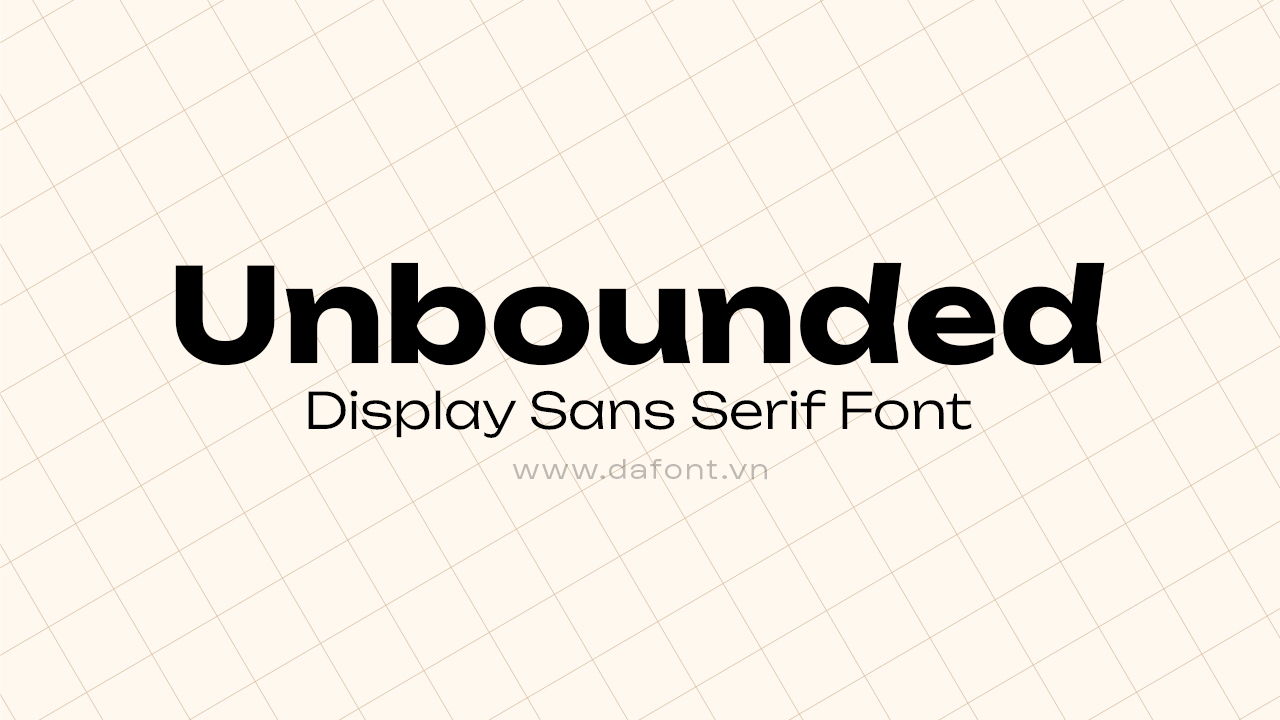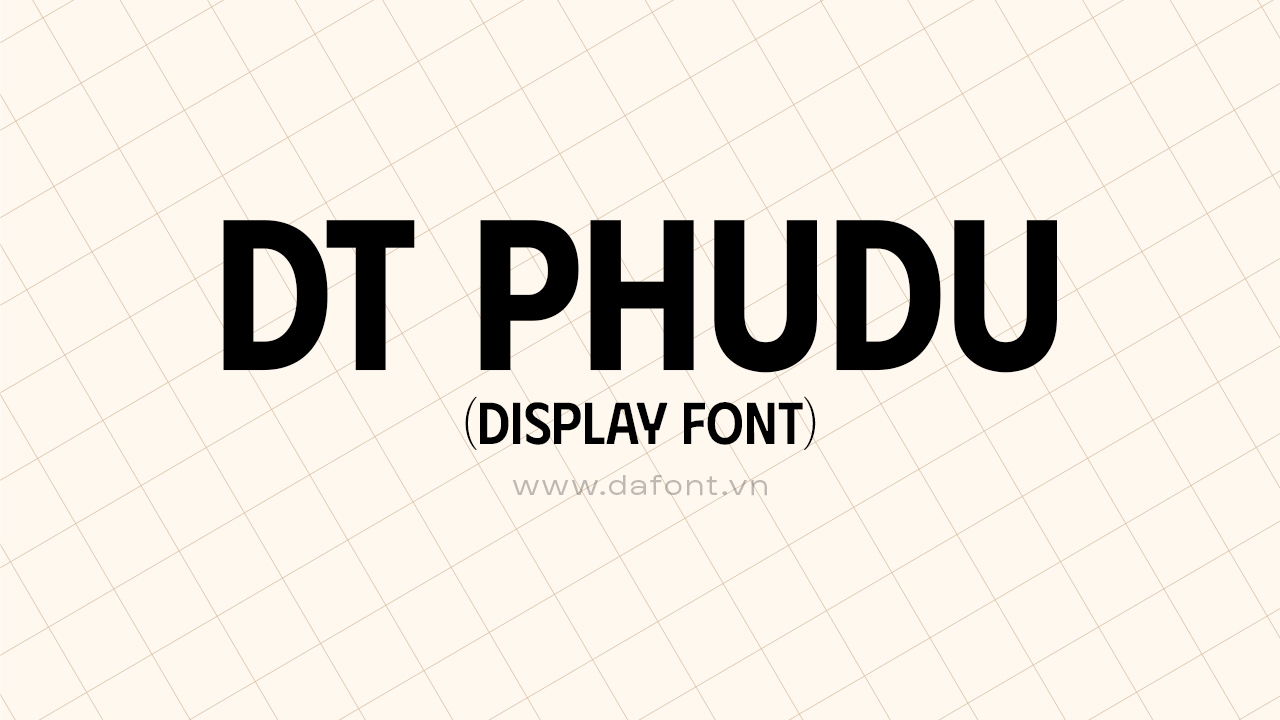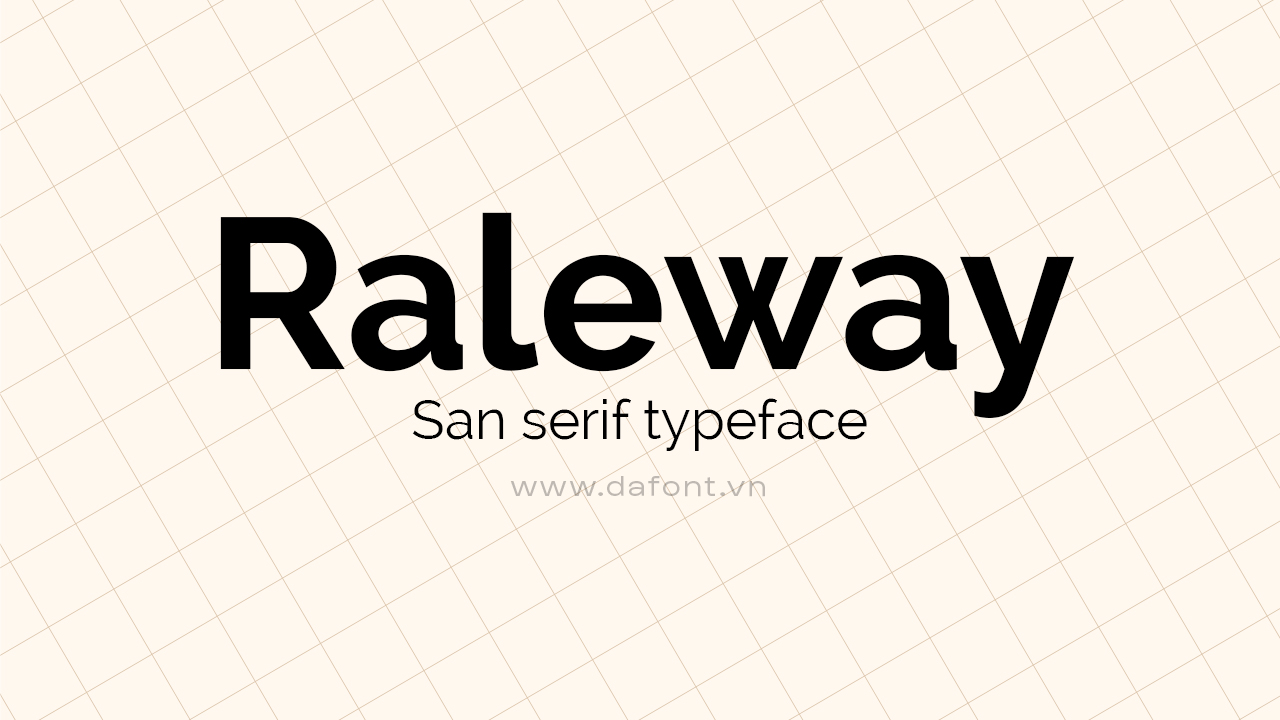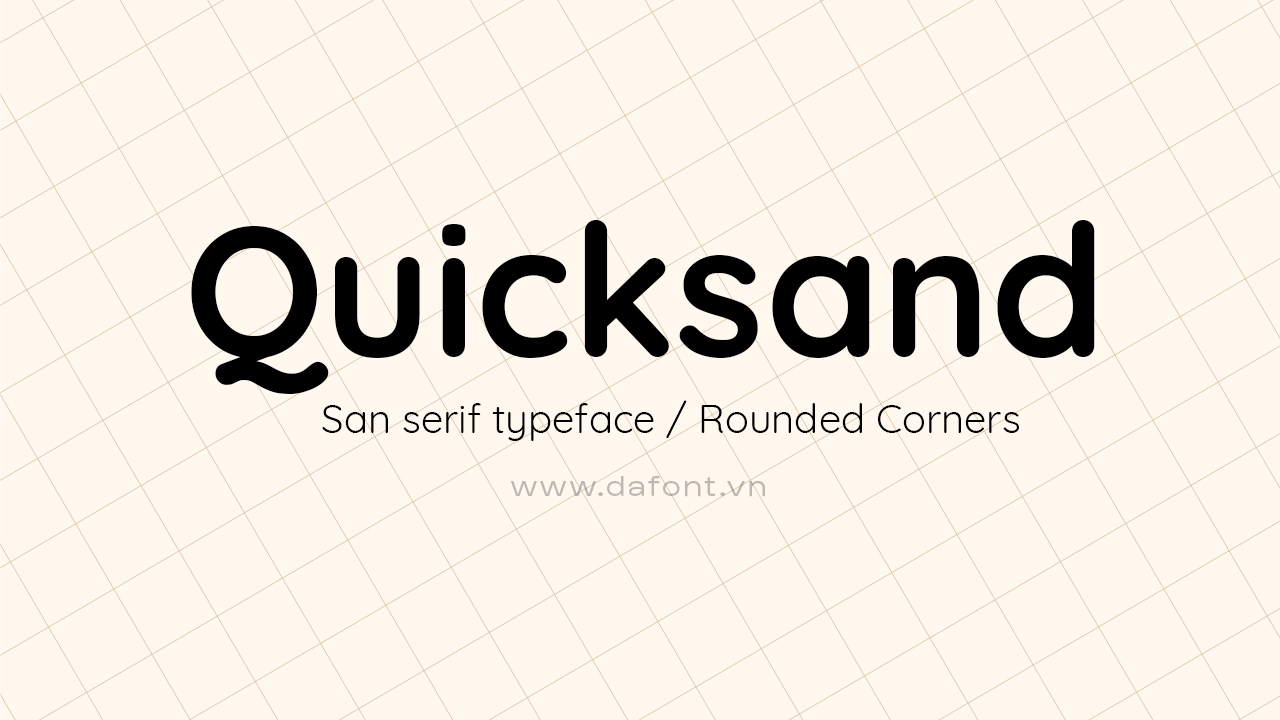
Trong thế giới thiết kế đồ họa, việc lựa chọn font chữ phù hợp không chỉ truyền đạt thông điệp một cách rõ ràng mà còn thể hiện phong cách và bản sắc riêng của thương hiệu. Google Fonts là một kho tàng font chữ miễn phí trở thành một nguồn tài nguyên vô giá cho các nhà thiết kế. Đặc biệt, với sự gia tăng của nội dung tiếng Việt trên internet, việc lựa chọn những font chữ hỗ trợ tiếng Việt là điều không thể thiếu. Vậy, font tiếng Việt nào thống trị Google Fonts. Hãy cùng khám phá nhé.
Google Fonts là gì?
Google Fonts là thư viện font chữ miễn phí được cung cấp bởi Google. Ra mắt vào năm 2010, nó đã nhanh chóng trở thành một công cụ quan trọng cho các nhà thiết kế web, nhà phát triển, nhà sáng tạo và cho bất kỳ ai muốn cải thiện giao diện văn bản trên các trang web, tài liệu, ứng dụng.
Những bộ font tiếng Việt phổ biến trên Google Fonts
Ngoài những font tiếng Việt đang thống trị Google, bạn cũng có thể khám phá nhiều font Việt hóa đẹp mắt, mang đến phong cách độc đáo và cá tính cho thiết kế của mình. Những font này không chỉ giúp nội dung trở nên sinh động, mà còn phù hợp với xu hướng thiết kế hiện đại, hỗ trợ đầy đủ dấu tiếng Việt để bạn thoải mái sáng tạo.
1. Montserrat
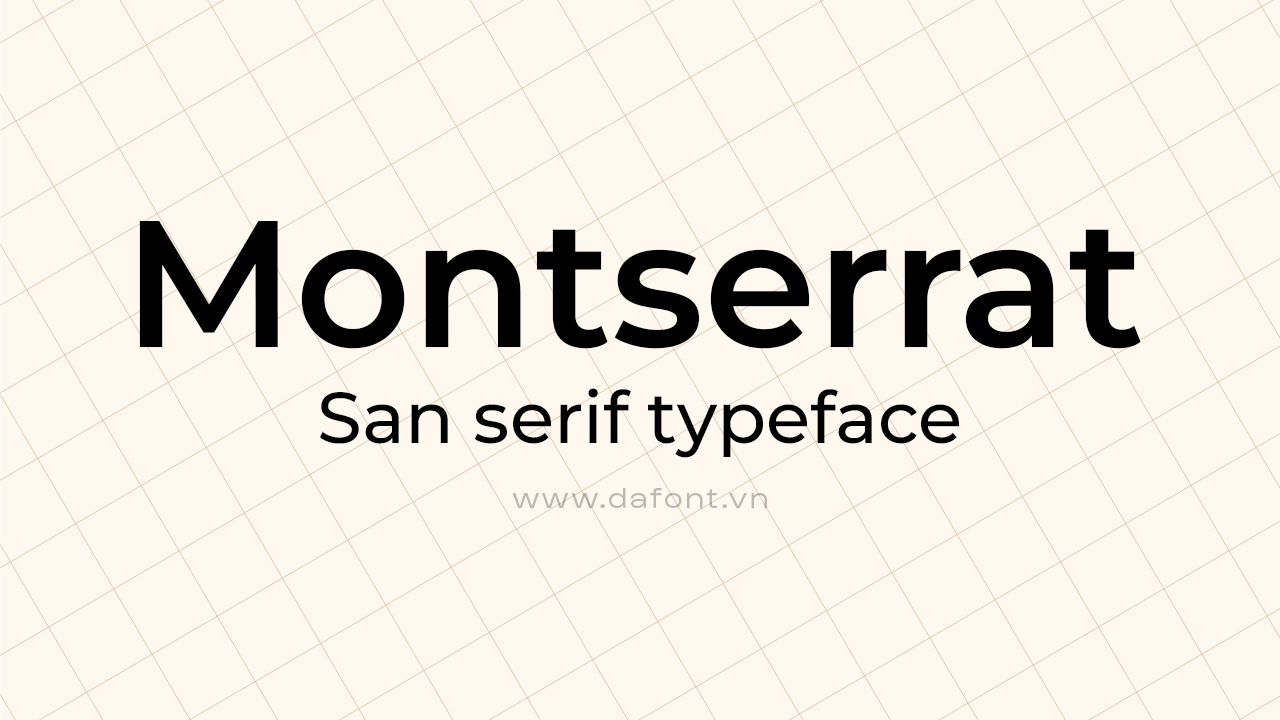
Montserrat là font chữ sans-serif hiện đại được thiết kế bởi Julieta Ulanovsky. Lấy cảm hứng từ các bảng hiệu và áp phích cổ điển ở khu phố Montserrat của Buenos Aires, Argentina. Font chữ này mang đến sự hòa quyện giữa vẻ đẹp truyền thống và tính thẩm mỹ hiện đại. Montserrat bao gồm 18 font và là một trong những bộ font chữ được ưu chuộng nhất trên Google Fonts.
2. Nunito
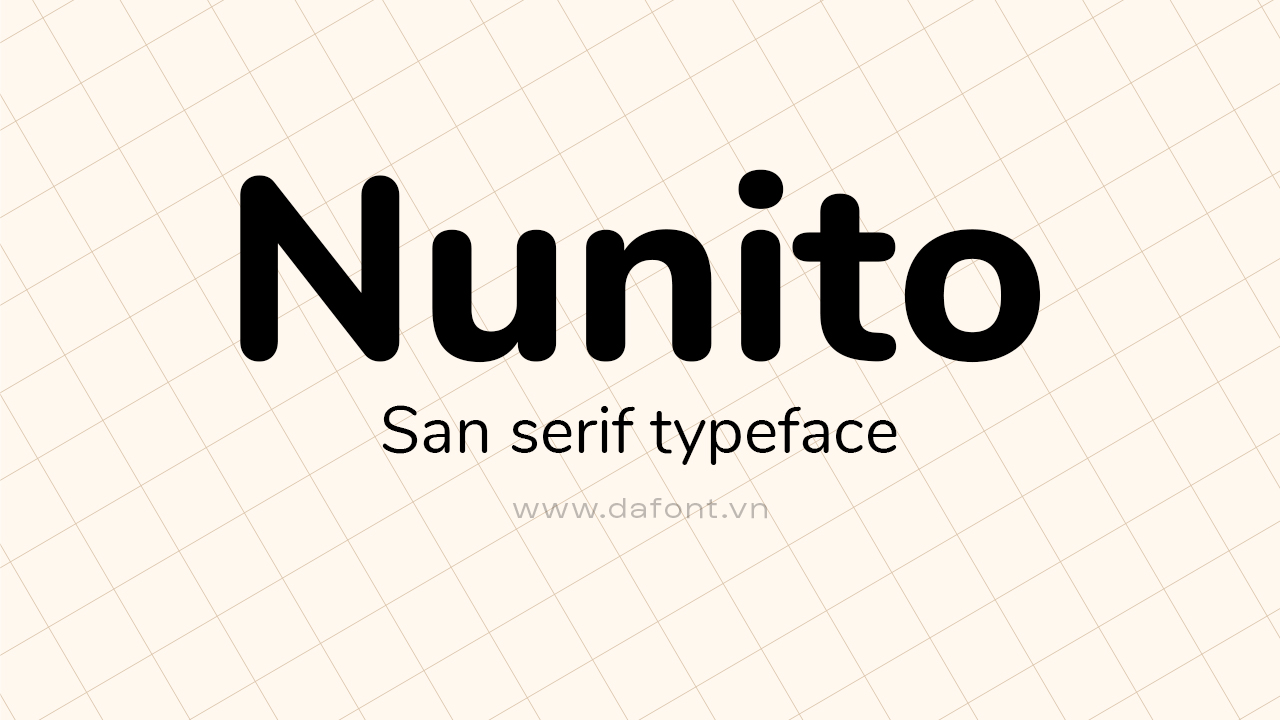
Nunito là bộ font chữ sans-serif có hai phiên bản: Nunito và Nunito Sans. Dự án này bắt đầu với Nunito, được tạo ra bởi Vernon Adams với thiết kế là font chữ sans-serif có đuôi tròn, phù hợp cho việc hiển thị typography. Sau đó, Jacques Le Bailly đã mở rộng dự án này bằng cách thêm vào một bộ trọng lượng đầy đủ và phiên bản không tròn đuôi, Nunito Sans.
3. Playfair
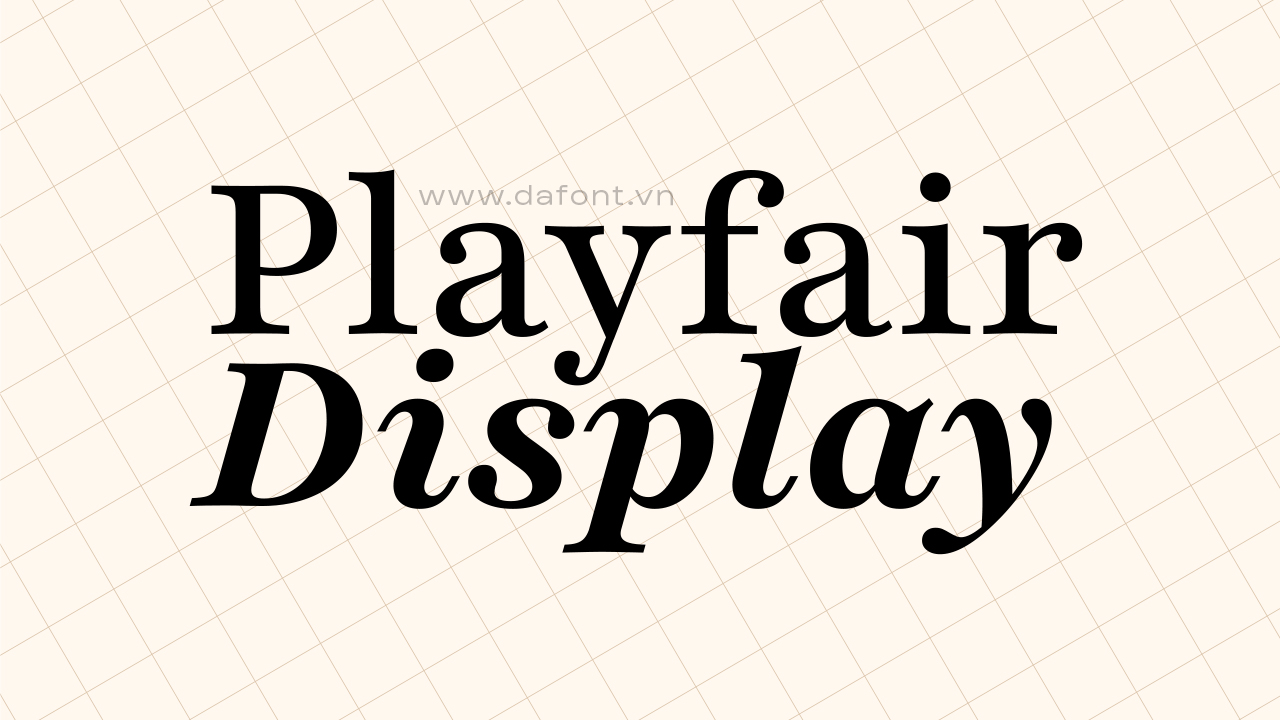
Playfair được thiết kế bởi Claus Eggers Sørensen, mang đậm dấu ấn của các kiểu chữ thế kỷ 18 trong thời kỳ Khai sáng (European Enlightenment) của Châu Âu, bút lông ngòi rộng đã được thay thế bằng bút thép nhọn như một công cụ viết phổ biến thời đó. Cùng với sự phát triển của công nghệ in ấn, mực in và sản xuất giấy, việc in các dạng chữ có độ tương phản cao và các đường nét mảnh ngày càng trở nên thời thượng, ngày càng tách rời khỏi các dạng chữ viết. Thiết kế này phù hợp với thời kỳ này và mặc dù nó không phải là sự hồi sinh của bất kỳ thiết kế cụ thể nào, nhưng nó chịu ảnh hưởng từ các thiết kế của John Baskerville và từ các thiết kế ‘Scotch Roman’.
Kiểu chữ này ban đầu được xuất bản vào năm 2011 và có bản cập nhật lớn vào năm 2017. Là một thiết kế Display (kích thước lớn) thuộc thể loại transitional, về mặt chức năng và phong cách, nó có thể đi kèm với Georgia hoặc Gelasio cho nội dung văn bản. Nó đã được thành công vào năm 2023 bởi thiết kế Playfair hoàn chỉnh, dưới dạng font chữ có thể biến thể (variable font) bao gồm các thiết kế văn bản nội dung theo trục kích thước quang học.
4. Be Vietnam Pro
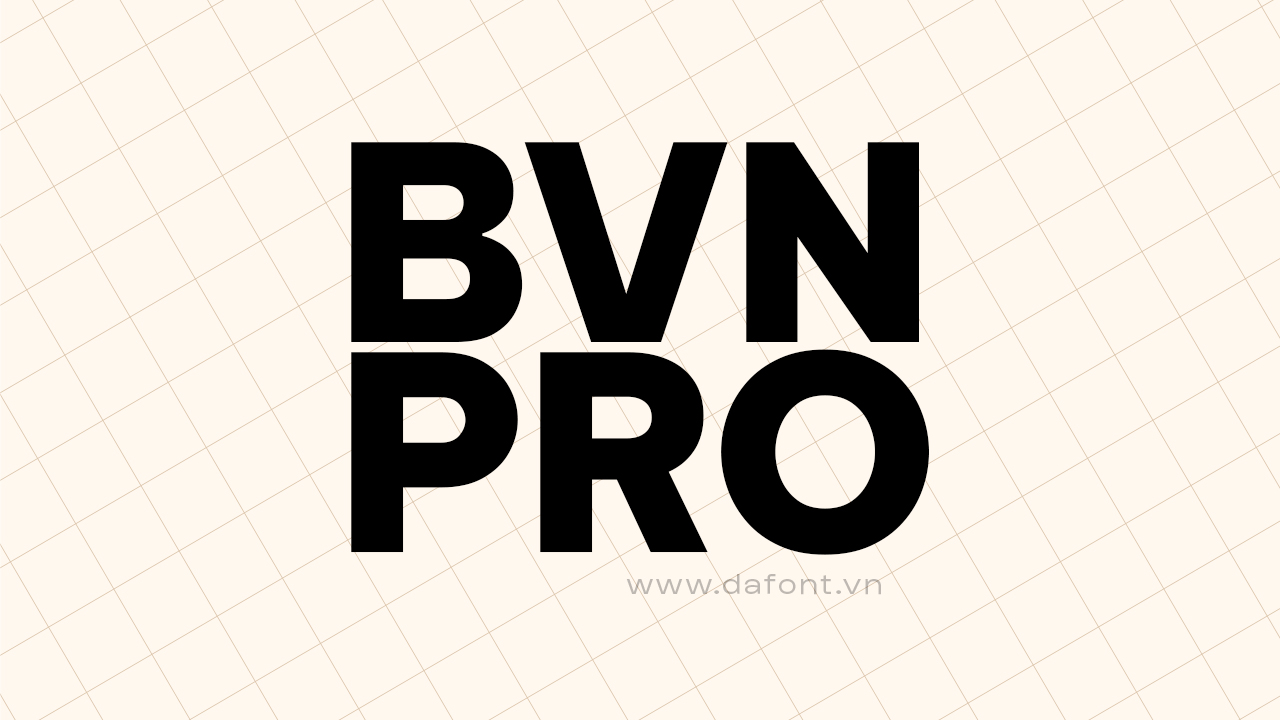
Be Vietnam Pro là bộ font chữ được thiết kế bởi Lâm Bảo, Nguyễn Đặng Việt Anh và Tony Le là một font chữ sans-serif hiện đại, được thiết kế đặc biệt để hỗ trợ tiếng Việt và các ngôn ngữ Latinh khác. Be Vietnam Pro mang đến sự kết hợp giữa tính thẩm mỹ cao và khả năng đọc tốt, làm cho nó trở thành lựa chọn phổ biến cho các dự án thiết kế web, in ấn, và giao diện người dùng.
Tới nay thì be Vietnam đã được sử dụng tổng cộng gần 60 triệu lượt trên khắp thế giới, trong đó có một số nơi đáng chú ý ở Việt Nam như các trang báo điện tử hàng đầu Việt Nam và tất nhiên là be, công ty công nghệ Việt Nam.
5. Manrope
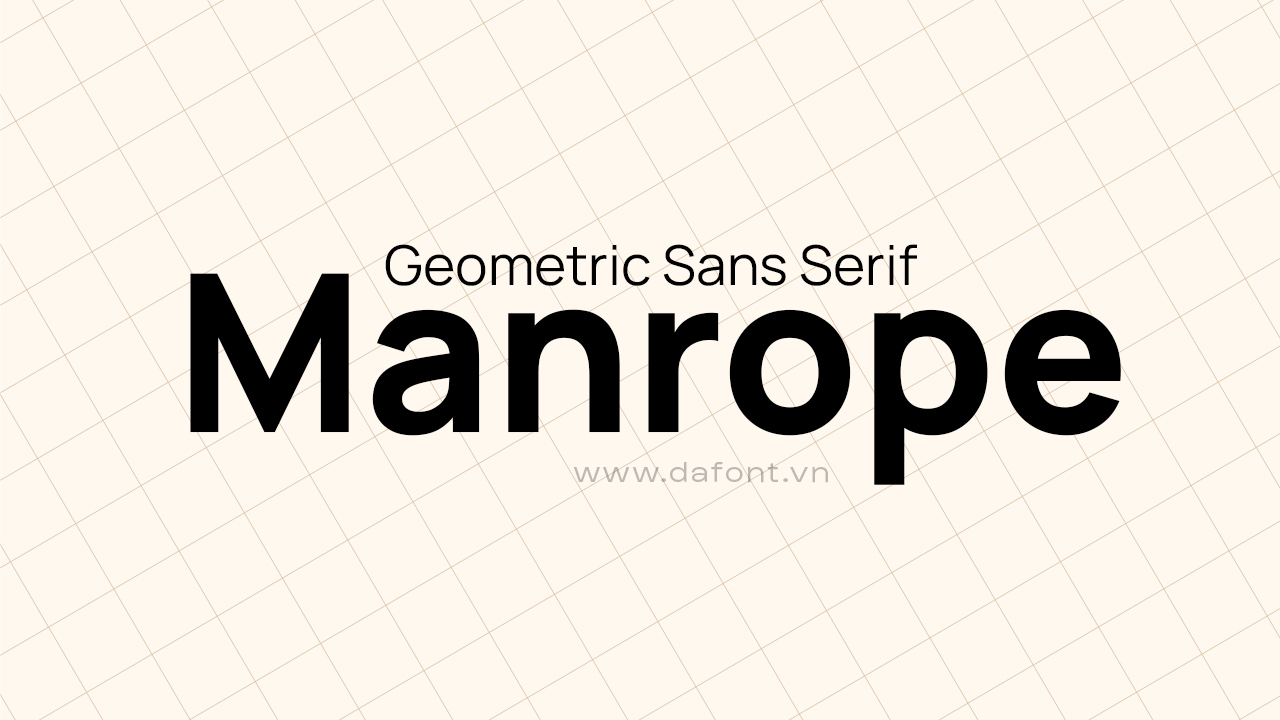
Manrope là một font chữ sans-serif hiện đại, thuộc dạng mã nguồn mở, được thiết kế bởi Mikhail Sharanda vào năm 2018. Vào năm 2019, Mirko Velimirovic đã hợp tác với Mikhail Sharanda để chuyển đổi Manrope thành một font chữ biến thể (variable font). Font chữ này hỗ trợ hầu hết các ngôn ngữ Latinh và Cyrillic.
6. Mulish
Mulish là một kiểu chữ sans-serif tối giản, được thiết kế để sử dụng cho cả văn bản và tiêu đề. Kiểu chữ này được Vernon Adams vẽ lần đầu vào năm 2011 và sau đó được hoàn thiện cho đến năm 2014, bổ sung thêm nhiều trọng lượng, hỗ trợ thêm nhiều ngôn ngữ Latin, cải thiện khoảng cách, kerning và tinh chỉnh nhiều chi tiết glyph dựa trên phản hồi của hàng trăm người dùng. Năm 2017, bộ font này được Jacques Le Bailly cập nhật để hoàn thành công việc mà Vernon đã bắt đầu sau khi ông qua đời, phối hợp với vợ ông là Allison, người giữ bản quyền. Vào tháng 8 năm 2019, Mulish được cập nhật thêm Variable Font.
7. Barlow
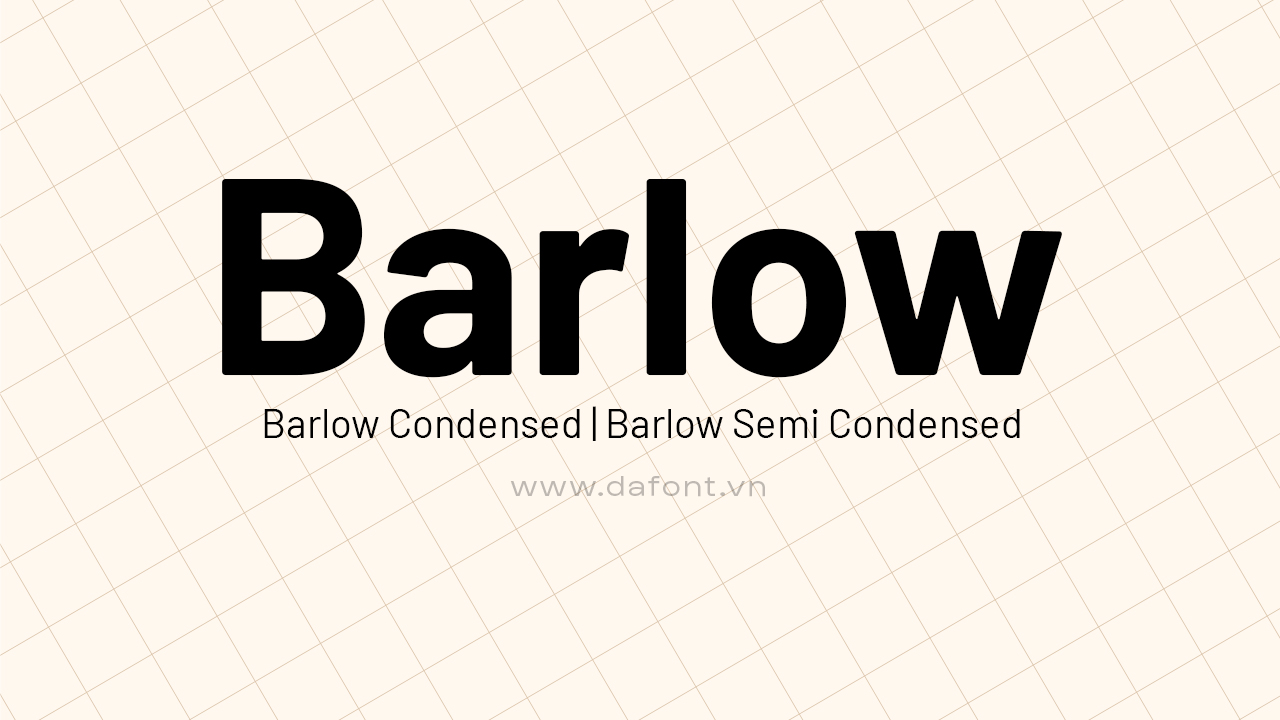
Barlow là một bộ font grotesk với đặc điểm là có các góc cạnh được bo tròn nhẹ, độ tương phản thấp. Phông chữ này lấy cảm hứng từ các địa điểm công cộng trên khắp California, với nhiều đặc điểm như biển số xe, biển báo đường cao tốc, xe buýt và tàu điện của tiểu bang này. Barlow là một dự án do Jeremy Tribby thiết kế.